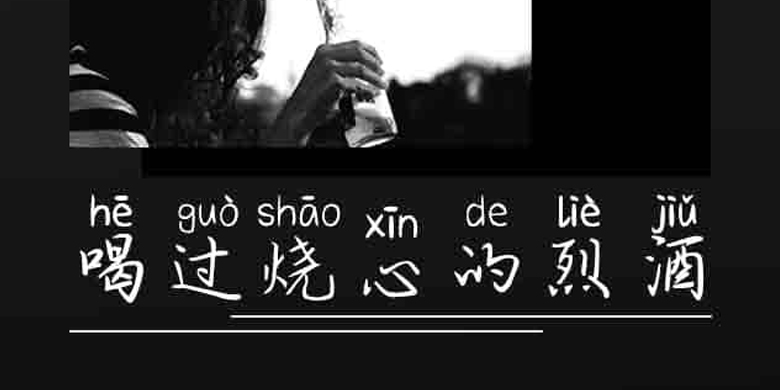
方正手迹-喝过烧心的烈酒
方正手迹-喝过烧心的烈酒,这款字体结构工整、笔画清晰,兼顾美观与易读性,适用于标题、正文、海报、包装、LOGO 等多种场景。字形优雅稳定,风格百搭耐看,适配日常排版与创意设计,让文字呈现更舒适、更具质感。方正手迹-喝过烧心的烈酒一笔一画,皆是细节,以均衡的比例、流畅的线条打造舒适视觉体验,字形端正大气,风格简约现代。无论是商业设计、品牌宣传还是日常排版,都能轻松驾驭,让文字更有格调与力量。方正手迹-喝过烧心的烈酒字体下载。
字体品牌: 方正手迹 设计师:俞亦婷 字体分类:创意书写 字体属性:精品字 字符集:大陆简体(GB2312-80) 发布时间: 2020
喝过烧心的烈酒拼音体,用笔考究,字形左右延伸,从容优雅,文艺气息浓厚。适用于文艺类的书刊、品牌广告和产品包装设计,以及社交网络的个性化用字。